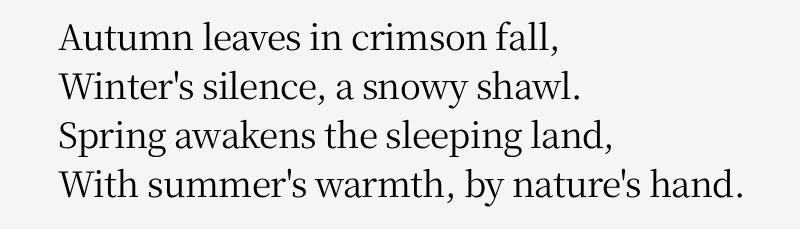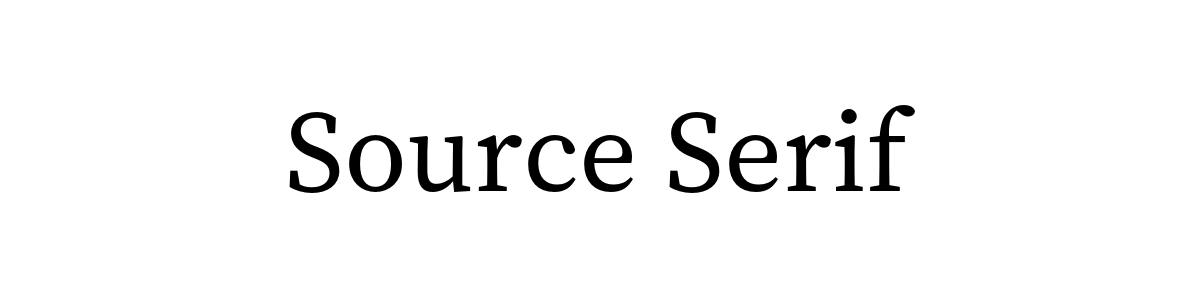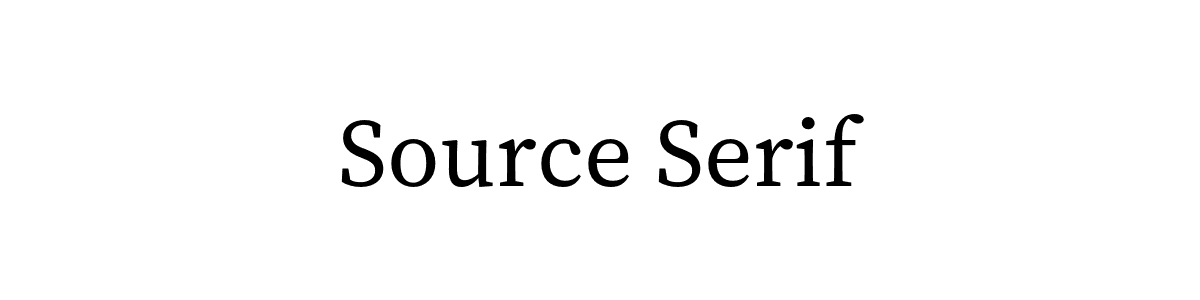
Source Serif
Source Serif 是 Adobe 在 2014 年推出的一款开源衬线字体,由知名设计师 Frank Grießhammer 完成主设计。它属于 Adobe Source 字体家族,不仅是思源宋体中西文部分的原型,自身也是一套完整成熟、广受好评的独立字体。
这款字体专门为长篇阅读优化,支持拉丁语、希腊语与西里尔字母,字重体系完整,包含 ExtraLight 到 Black 七种粗细,并且每一款字重都配有对应的意大利斜体,排版选择十分丰富。
字体风格
Source Serif 定位为数字与印刷环境都适用的正文型衬线体,笔画粗细对比适中,字腔开阔舒展,在小字号和屏幕上依然保持优秀的可读性。
整体气质兼具理性清晰与人文温度,适合书籍、论文、报告等需要长时间阅读的文本,也常用于品牌设计中传递经典、稳重、可靠的印象。因为和思源宋体的西文同源,两者搭配使用时视觉高度统一,多语言混排效果尤为和谐专业。